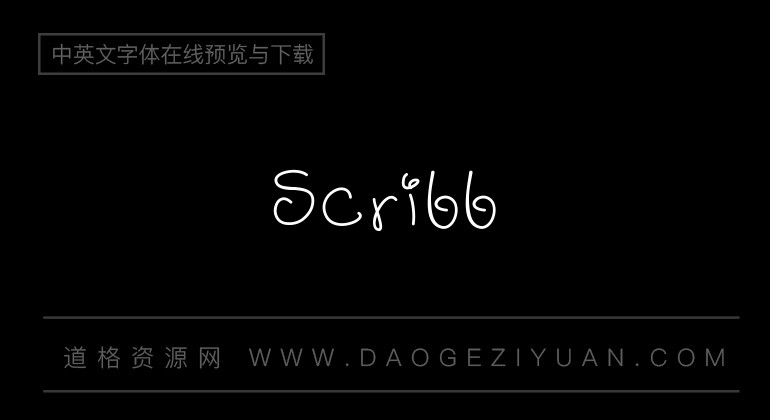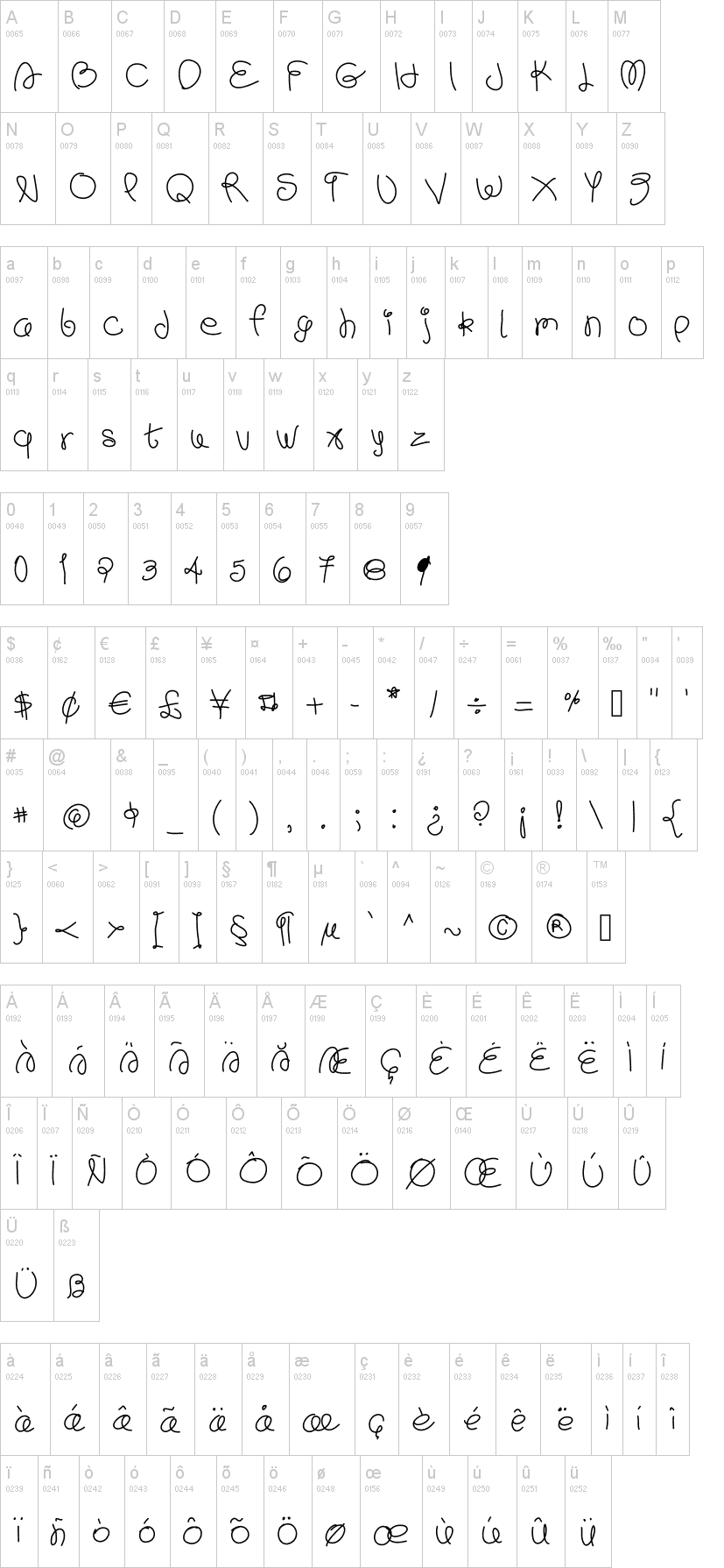
Scribb 是一款新的字体,由英国设计师 James T. Edmondson 设计。它是一款非常细腻、精致的字体,具有流畅的线条和清晰的字形,适用于各种大小的文本和标题。它的字母和字形都非常细腻,但又不失优雅,可以满足各种应用场景的需求。它的字形比较紧凑,可以节省空间,适合用于网页设计,报纸、杂志等印刷品的设计,也可以用于品牌标志的制作。内容介绍
Scribb是一款非常不错的手写艺术字体,具有很好的视觉感,适合于文化类的宣传设计、商业类品牌的广告和产品包装设计以及个性化文字排版等较多场景。